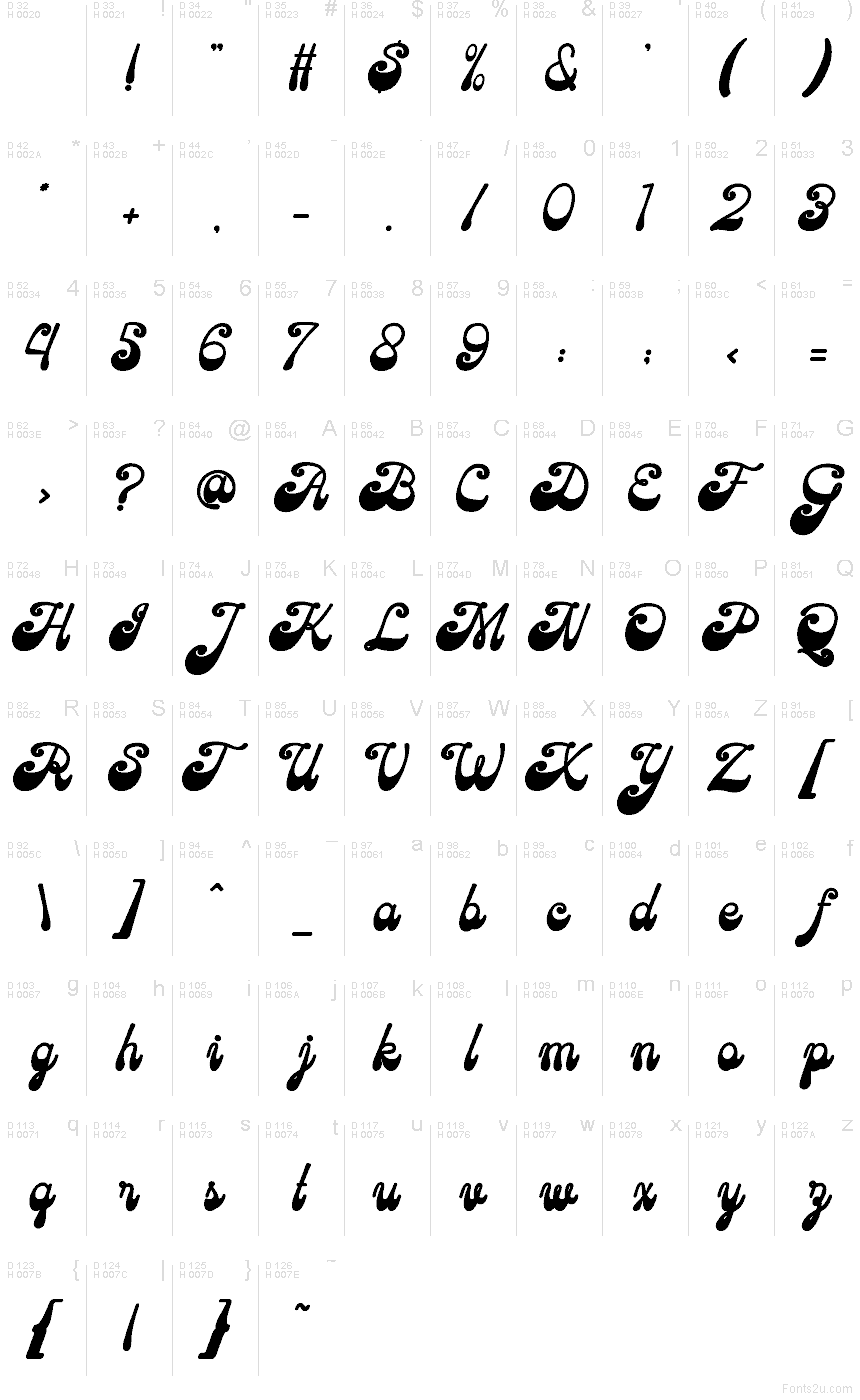
تعد خط Chunk Five من Putracetol Studio خط فرشاة مجاني يتميز بمنحنيات عريضة ولامعة وإيقاع كتابة يدوية انسيابي. تتأرجح الحروف بين خطوط عمودية مرتفعة وقواعد عميقة تشبه القطرات، مما يمنح الخط ملمساً ناعماً ومليئاً بالحبر، بعيداً عن القوام الجاف لفرشاة الرسم التقليدية.
هذا الانسياب الدائري يجعل من Chunk Five خياراً طبيعياً لشعارات المقاهي، وتغليف المنتجات، وعناوين الملصقات، وترويسات وسائل التواصل الاجتماعي، والعلامات التجارية غير الرسمية. وتبرز جمالية الخط بشكل خاص في العبارات القصيرة، حيث تعمل الوصلات المنسابة والمنحنيات السفلية الكبيرة على إبراز الاسم أو الشعار بشكل جذاب دون أن يبدو جامداً.